Untuk membuat tipografi dalam desain grafis tampil menarik dan membantu menyampaikan pesan dengan efektif, gunakan tools atau website yang tepat. Ada banyak website dengan berbagai tools yang membantu melihat kecocokan kombinasi font dan variasi font menarik. Website dan tools yang menyediakan berbagai style tipografi dan font akan berguna untuk desainer grafis.
Manfaatkan berbagai jenis website untuk tipografi dan font untuk membuat teks mudah dibaca dan memiliki gaya huruf menarik. Dalam desain grafis, teks harus tampil menarik dengan dimodifikasi dan dikombinasikan dengan gaya font yang tepat. Setiap jenis font dan gaya yang berbeda bisa menciptakan kesan dan nuansa yang berbeda, seperti:
- Serif untuk desain bergaya klasik, formal dan sederhana
- Sans serif menciptakan tampilan modern, bold dan elegan
- Script dengan huruf latin bisa menciptakan kesan elegan dan mewah.
- Monospace yang tampil klasik dan berkesan vintage
- Decorative sering digunakan untuk menciptakan tampilan unik dan kreatif.
- Handwriting biasanya menciptakan kesan alami dan organik.
Memilih jenis font dalam desain harus mempertimbangkan beberapa hal tersebut termasuk makna psikologi yang diciptakan. Kombinasi dua font dapat menciptakan pula makna dan kesan yang berbeda.
7 TOOLS FONT DAN TIPOGRAFI MENARIK
Dalam memilih font yang cocok untuk digunakan dalam desain grafis, pertimbangkan melihat kesesuaian teks dan kombinasi font dalam berbagai website. Ada banyak tools menarik untuk melihat teks, mengkombinasikan font hingga membuat font sendiri. Berikut website dengan berbagai tools yang menarik untuk memilih font yang tepat dalam desain;
Fontspace
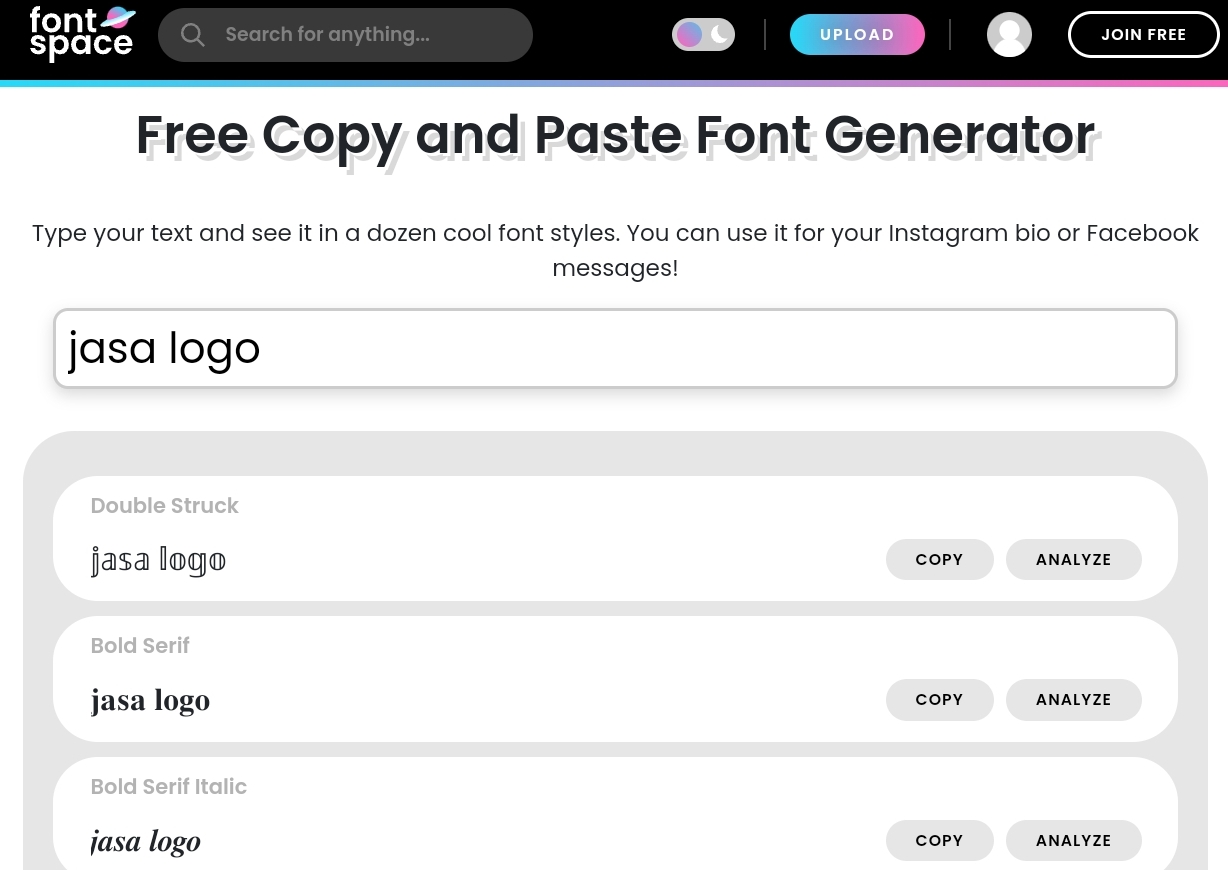
Dalam website ini kamu bisa mendapatkan berbagai jenis font dengan berbagai jenis dan gaya yang menarik. Pada website ini desainer bisa mengecek teks yang digunakan dalam berbagai jenis font. Selain bisa melihat teks dalam font tertentu, desainer juga bisa mengatur warna teks sesuai kebutuhan.
Ada juga fitur yang membantu desainer mendapatkan rekomendasi berdasarkan kebutuhan atau gaya font seperti weddings, funky dan futuristik. Ada banyak style desain yang tersedia untuk digunakan sesuai kebutuhan tema desain.
Fontpair
Untuk website fontpair ini kamu bisa mencari pasangan yang cocok dari jenis font yang ingin kamu gunakan. Sayangnya kebanyakan font yang dipasangkan dalam website ini hanya serif dan sans serif. Kamu bisa mencari font tertentu dan akan muncul banyak rekomendasi font pairing.
Tidak hanya melihat kecocokan font tetapi kamu juga bisa mengganti teks dengan teks milikmu. Kombinasi font yang disediakan dalam web ini akan cocok untuk digunakan pada desain yang ingin menggunakan banyak teks.
Fontjoy
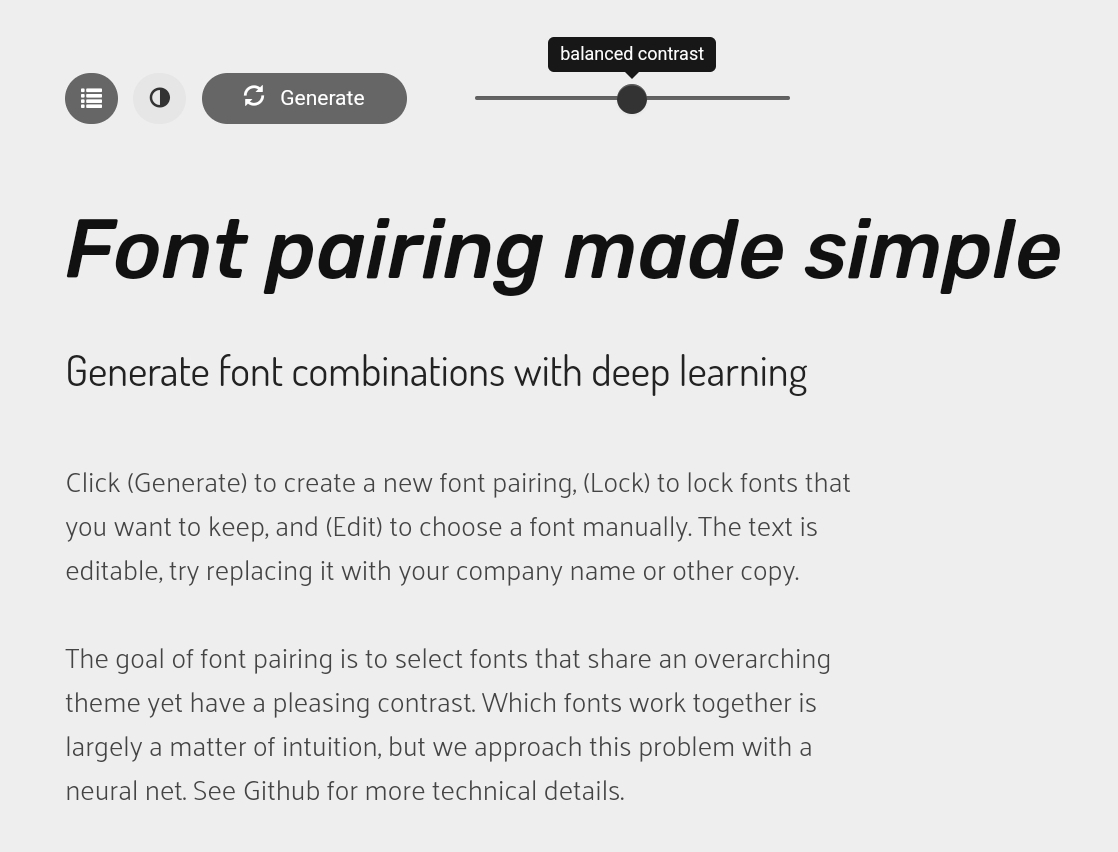
Dalam website ini juga menyediakan fitur untuk melihat tiga kombinasi font berbeda jika dikombinasikan. Tersedia tools untuk memilih gaya font dengan berbagai ketebalan Setiap font dalam headline, sub judul dan paragraf memiliki puluhan gaya font.
Beberapa pilihan yang tersedia tidak hanya memvariasikan ketebalan tetapi juga gaya serif hingga outline. Tools generate akan membantu mengubah gaya font untuk menemukan yang paling sesuai dengan kebutuhan desainer.
Typescale
Website satu ini memiliki tools yang lebih beragam dan dapat membantu memilih jenis font yang tepat. Kamu bisa mengecek keterbacaan dan tampilan berbagai jenis font ketika digunakan dalam desain. Desainer bisa melihat tampilan font jika digunakan pada landing website atau postingan blog.
Tools dalam web ini membantu desainer melihat keterbacaan teks dengan mengatur warna teks, background, ukuran hingga spasi dan skala font. Berbagai tools ini membantu desainer melihat apakah jenis font sesuai kebutuhan atau tidak. Tidak melihat tampilan dalam desain website tetapi juga membantu menentukan ukuran dan kontras warna teks yang baik.
Monotype
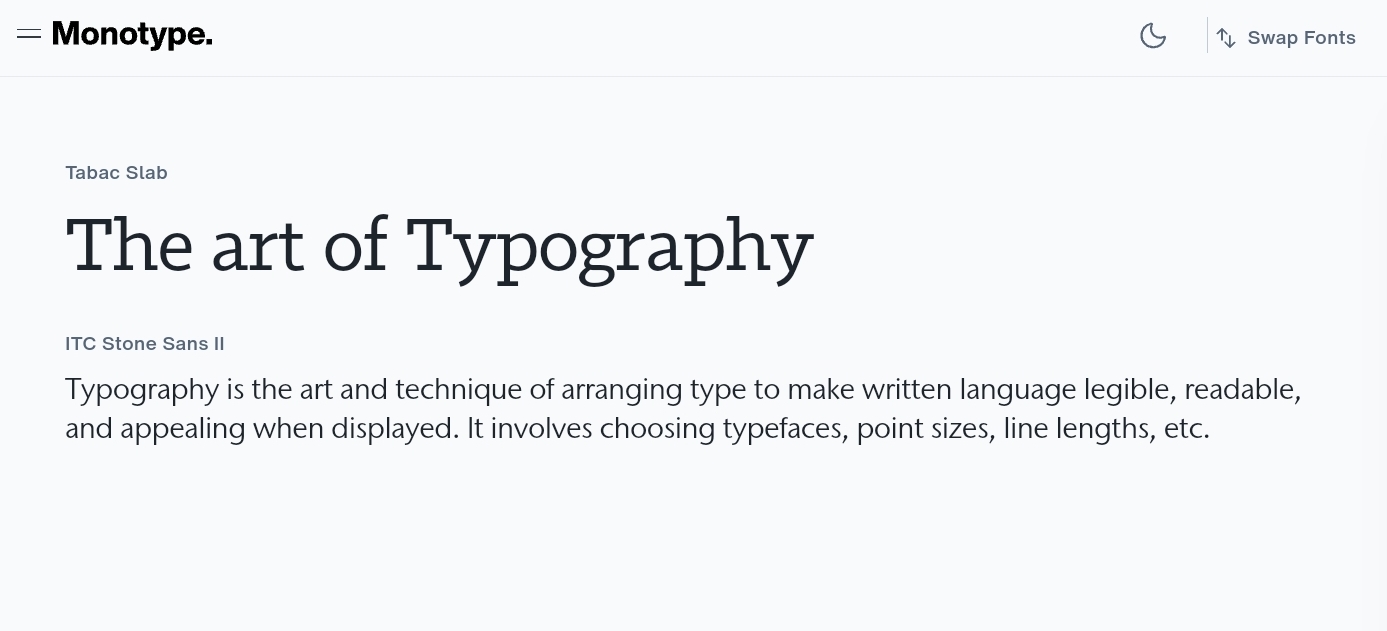
Tools dalam website ini menyediakan fitur untuk mencari kombinasi font yang harmonis. Ada banyak kombinasi dua font yang bisa digunakan dan dipilih untuk berbagai desain. Pilih kombinasi font yang sesuai dengan tema desain atau kebutuhan desainmu.
Tools ini juga menyediakan fitur untuk mengecek kombinasi font sesuai teks milikmu. Jenis font juga bisa diubah dan diatur ukurannya untuk melihat tampilan dari kombinasi font tersebut.
CARA EFEKTIF MEMILIH FONT DAN KOMBINASI YANG HARMONIS
Ketika menciptakan desain grafis pemilihan font dan kombinasi fontnya harus merepresentasikan gaya desain. Font juga perlu mudah dibaca sehingga membantu mengkomunikasikan informasi dengan baik. Ketika memilih font perhatikan beberapa hal ini agar sesuai dengan kebutuhan desain:
Pahami Jenis Font dan Kombinasinya
Sebelum memilih jenis font untuk digunakan dalam desain grafis, ada baiknya untuk desainer memahami berbagai jenis font terlebih dahulu. Umumnya jenis font memiliki banyak variasi seperti serif, sans serif, display, decorative, monospace, handwriting dan script.
Font yang digunakan dalam desain grafis harus dipilih dengan memerhatikan jenis font dan kesan yang diciptakan dari font tersebut. Untuk memilih font ada banyak cara yang bisa digunakan seperti memanfaatkan berbagai tools dalam website seperti fontjoy atau fontspace. Berbagai tools akan membantu untuk mengkombinasikan jenis font, mengecek tampilan font hingga keterbacaan font dalam berbagai skala.